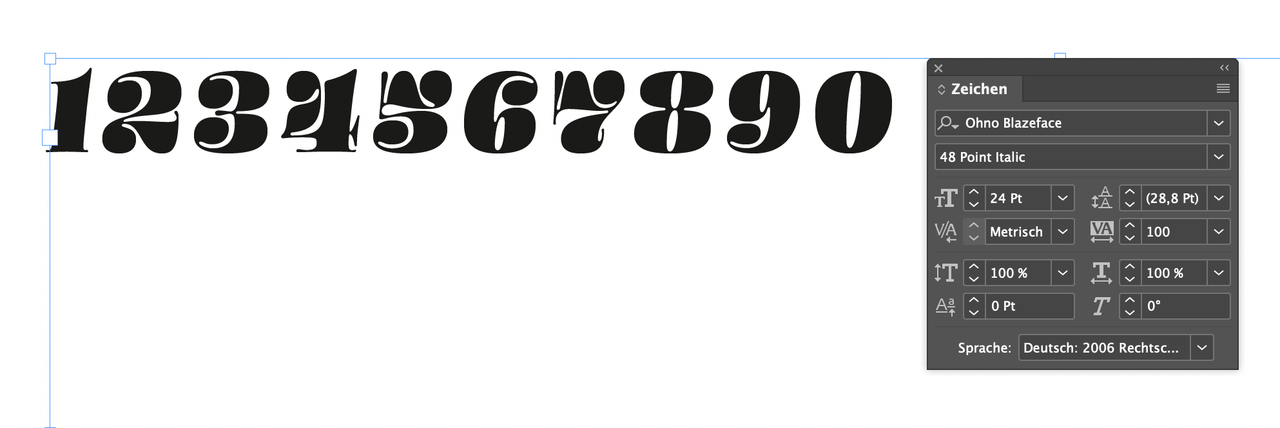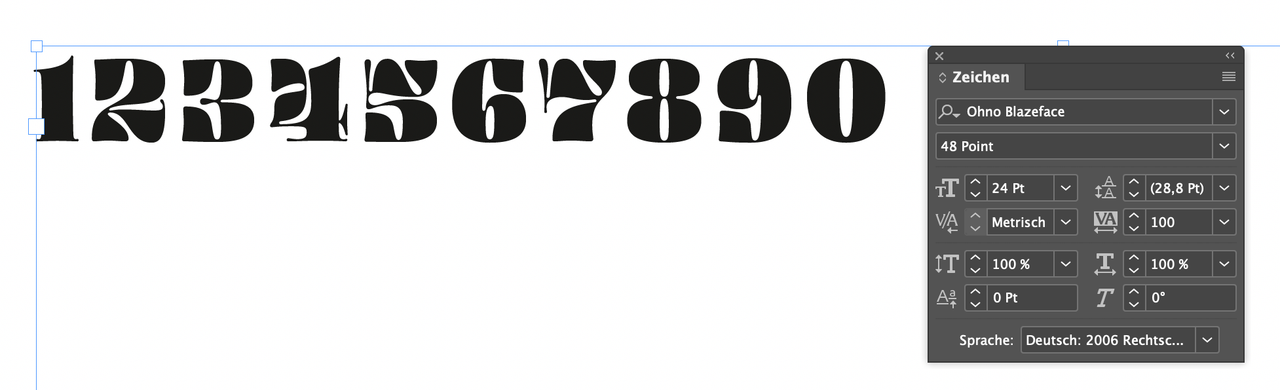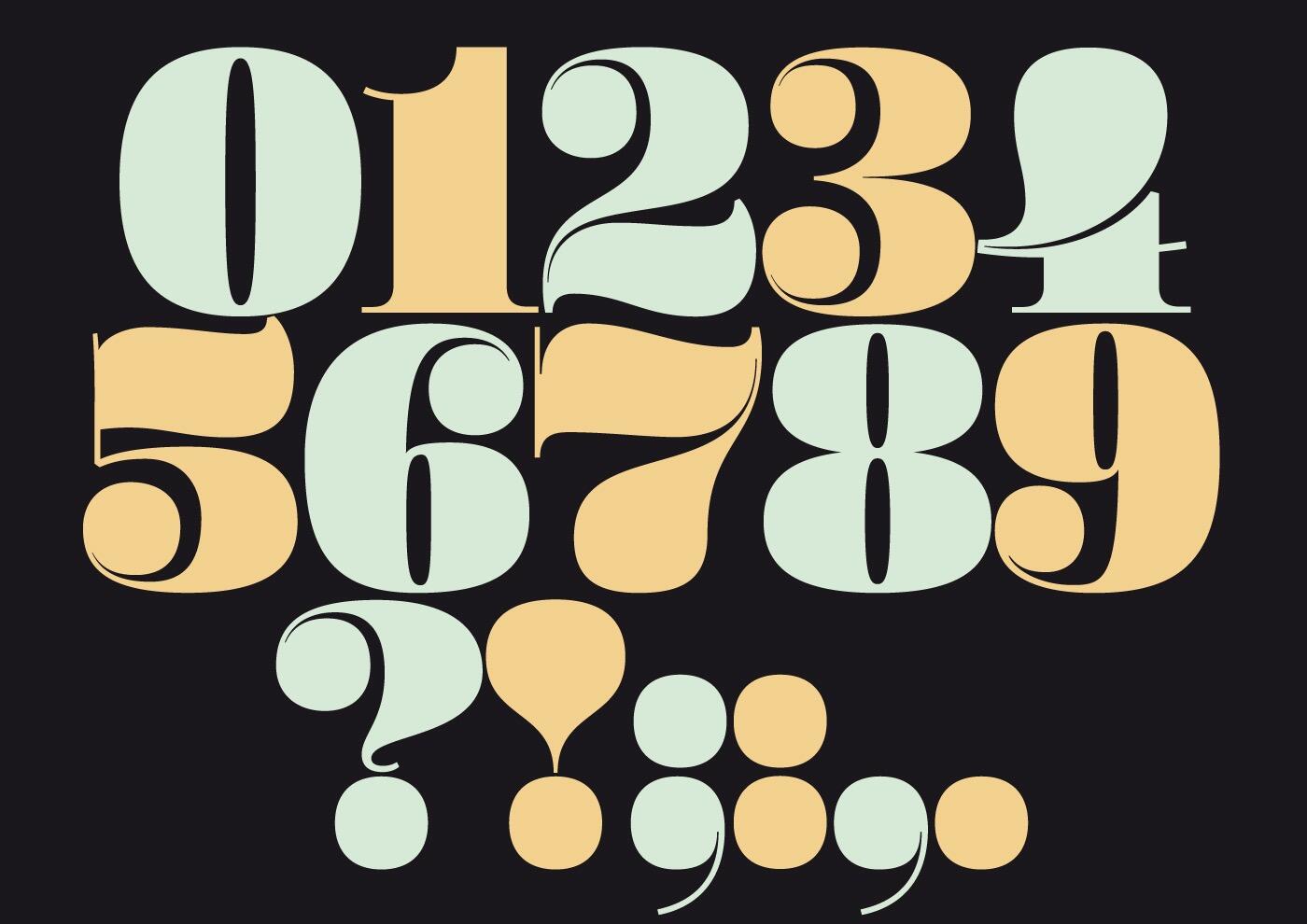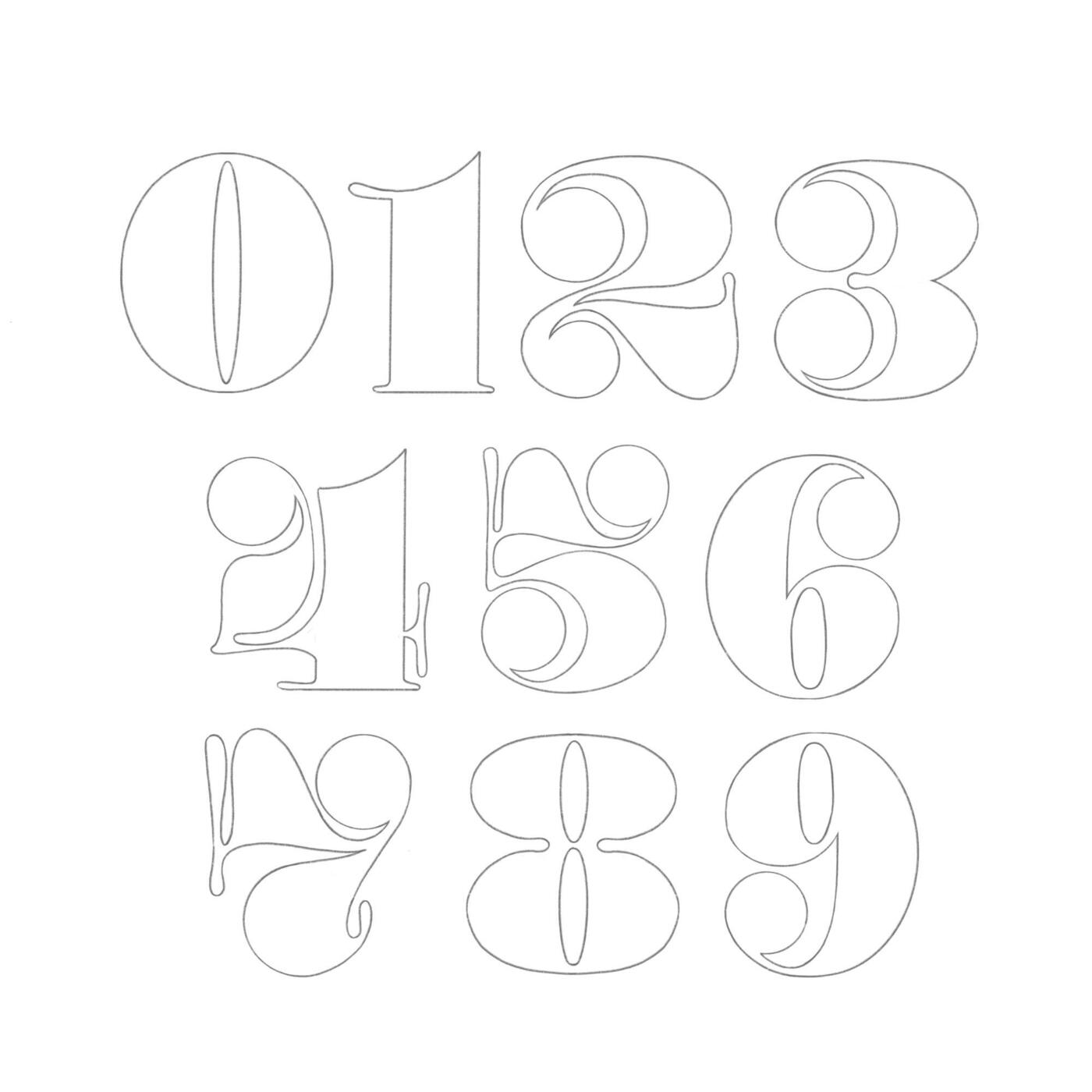
Bold Didone in Gestaltungs- Set entdeckt
als Bestandteil eines Gestaltungsset fand ich bei einem Online - Anbieter eine sehr interessante Schrift, die mich sehr an die früheren 70'er erinnert und perfekt für die Gestaltung von Illustrationen eben für diese Zeit geeignet ist.
Gefunden habe ich im Netz schon viel über diese Schrift (die Suche hier im Forum wollte diesbezüglich nicht so klappen, siehe Abb.), aber mir geht es speziell um diese wirklich „schrullige“ Version dieser klassischen Serifenschrift (siehe Abbildung, Bestandteil des Gestaltungsset, leider nur Ziffern).
Ich vermute, das hier ein kreativer Font - Designer diesen Stil gestaltet hat, oder gibt es diese sehr gelungene Art tatsächlich?
ja, „Fatface“ kommt dieser Schrift sehr nahe, selbst der Name ist wie geschaffen dafür!
Also sind die Beispiele, wie @Carlito Palm und ich sie genannt haben weitere gelungeneKreationen von geübten Schrift - Designer für Gestaltungszwecke und haben keinen festen Platz im Schriftensystem.
Ich finde diese und ähnliche Schriften sehr interessant, geben sie doch viel Spielraum für die weitere Gestaltung in der Grafik und damit meine ich natürlich nicht das optische „Verzerren“, was viele Kreative mit ihren Werken Schreckliches den Schriften antun, sondern mehr die farbliche und stilistische Interpretation.